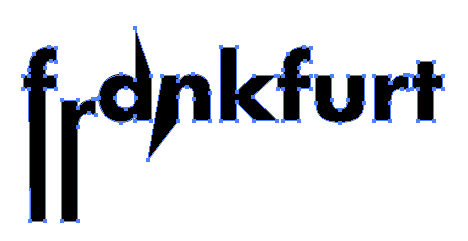
Schrift Frankfurt?
Ich habe in InDesign versucht z.B. das "f" mit der Futura Bold nachzubauen, ich kann es aber nicht so strecken?!
Eine Streckung des gesamten Zeichens liefert sicher nicht das gewünschte Ergebnis. Vielmehr musst Du die Buchstaben in einem Vektorgraphik-Editor (zB Illustrator) in Vektorpfade wandeln und diese dann bearbeiten. Beim "f" etwa die beiden Ankerpunkte unten rechts und links nach unten verschieben.
Das geht auch mit InDesign: Text markieren Shift-Apfel-O und dann mit dem weißen Pfeil bearbeiten  :nicken: